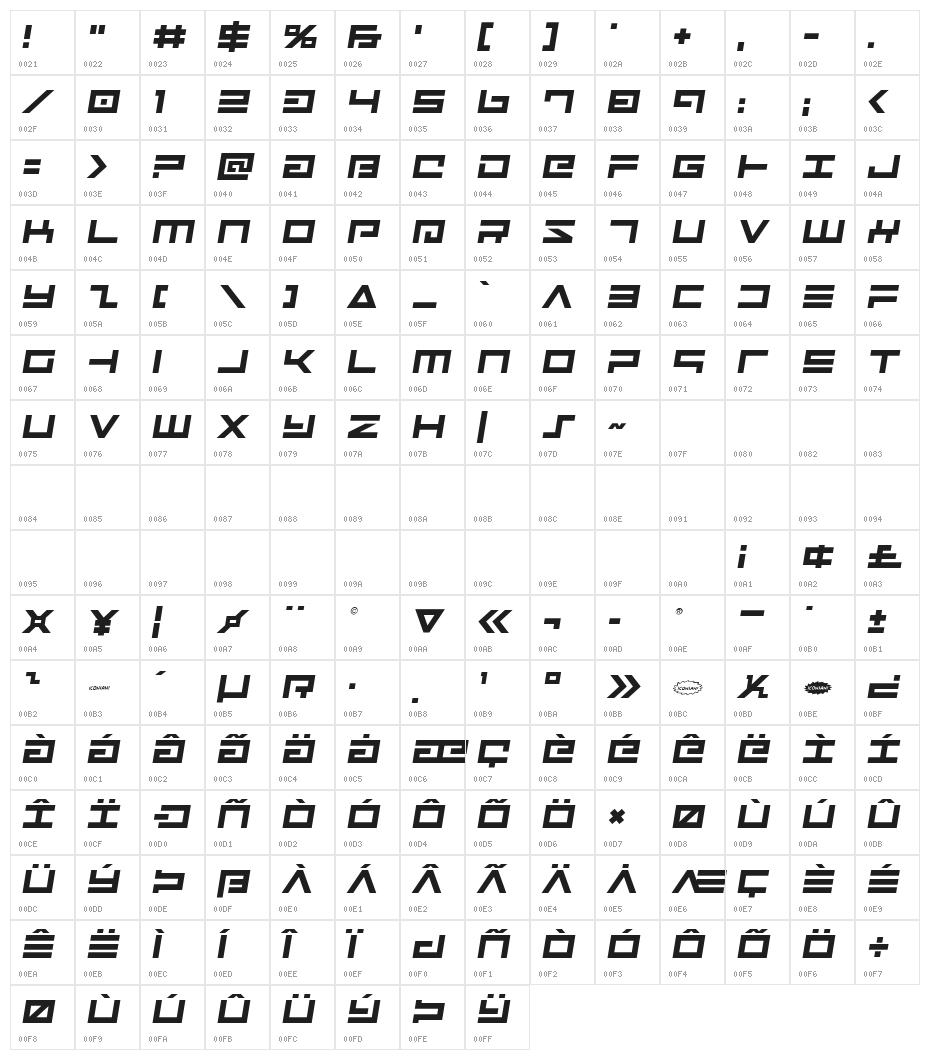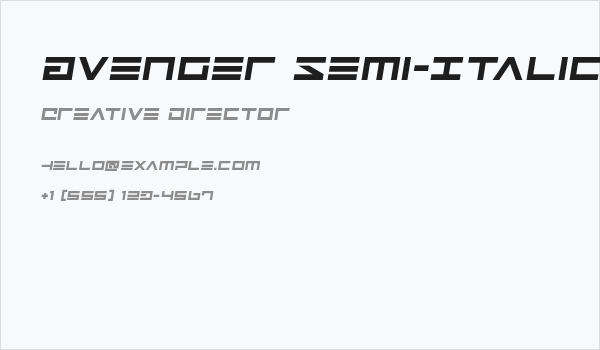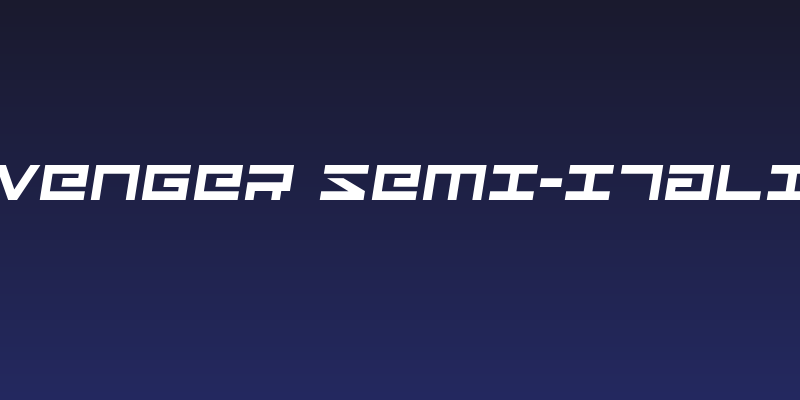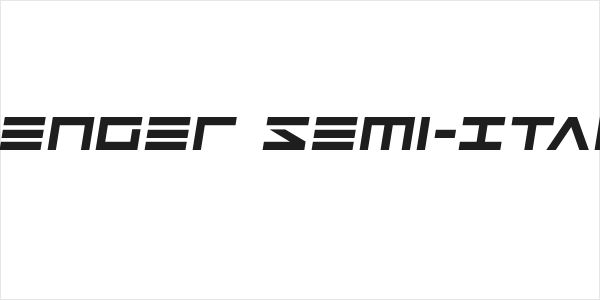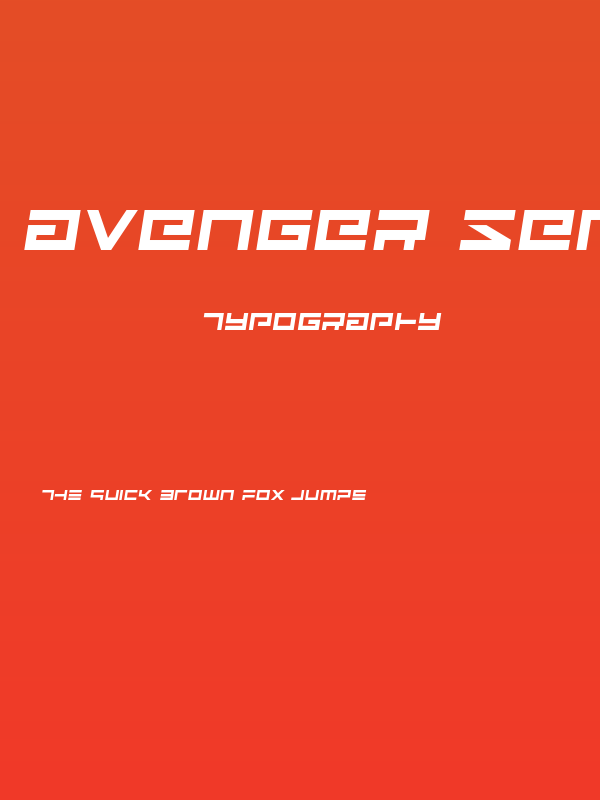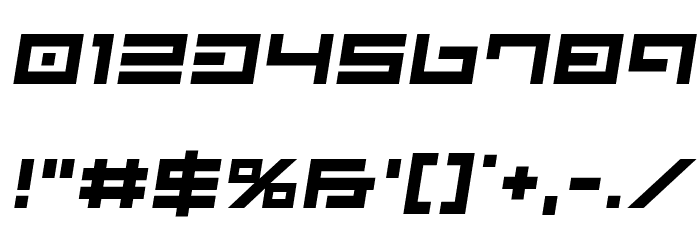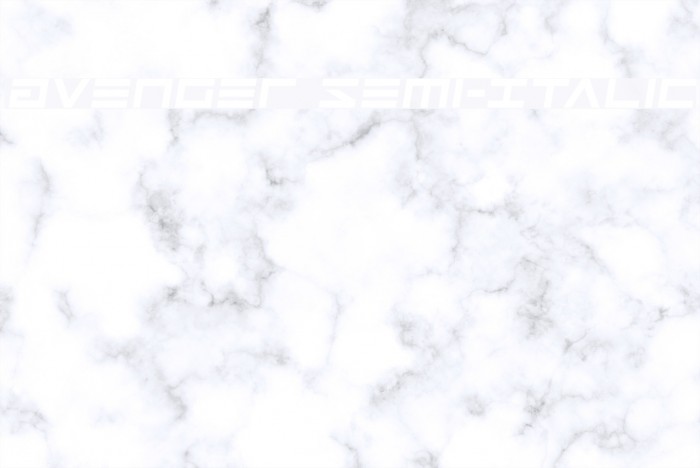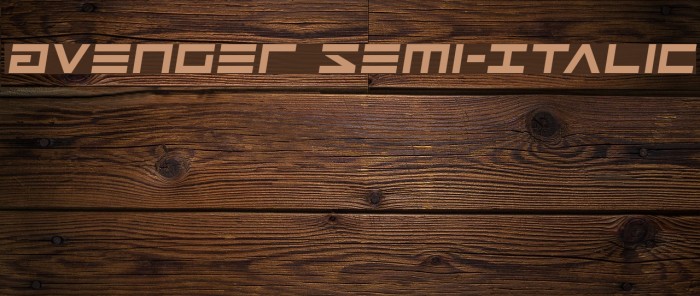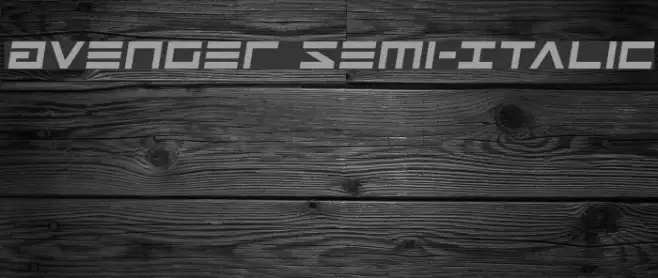
Avenger Semi-Italic Font
| Estilo general | Futuristic, Dynamic |
| Proyectos propuestos | Ideal for sci-fi themed projects, tech company branding, video game titles, or futuristic posters. |